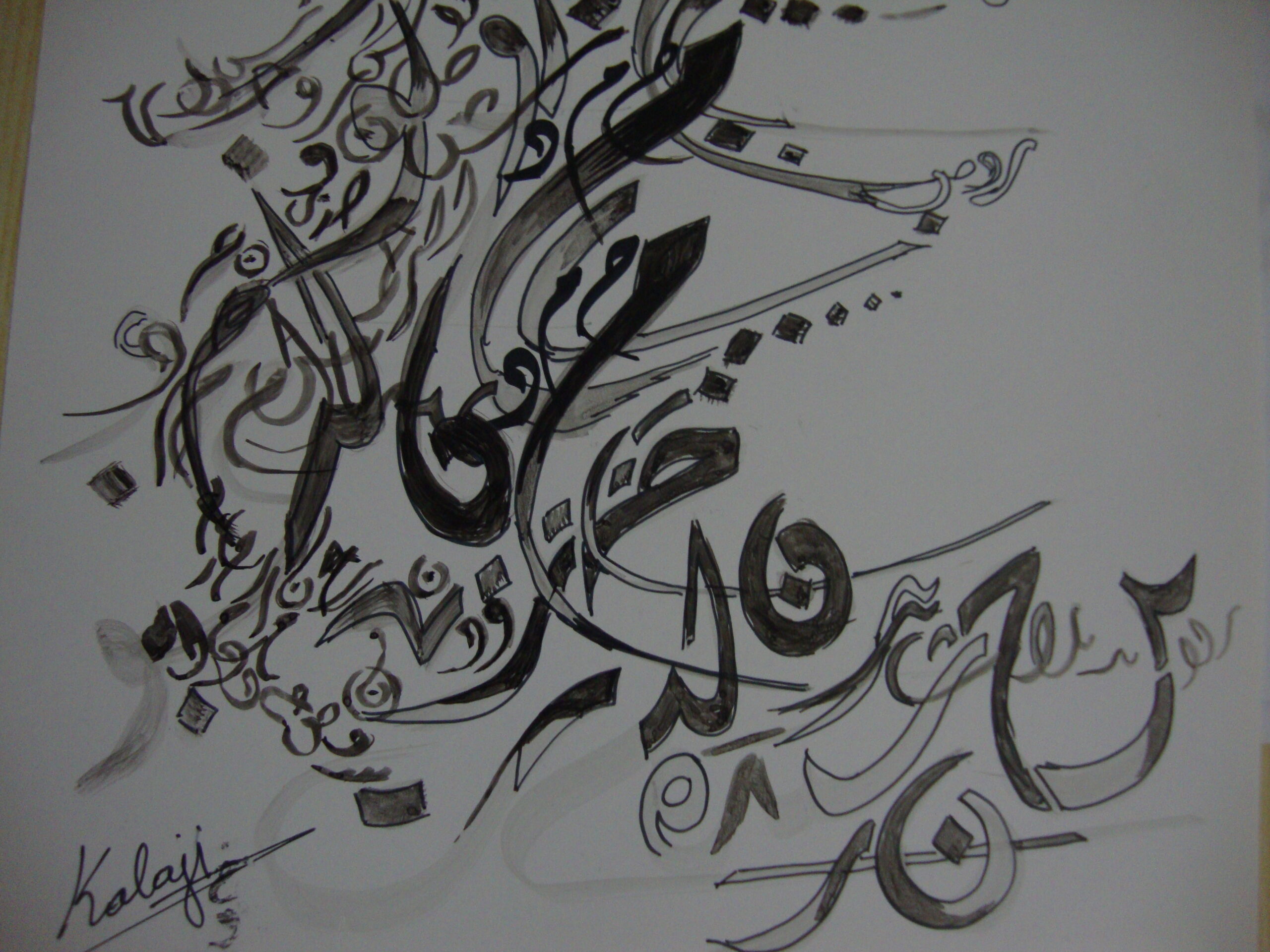
Visual Embedding of Calligraphic Ornamentation in Contemporary Art: A Dialectic of the Letter’s Memory and the Dynamics of Its Circulation
ملخص: تبدو الحروفية مسمى تشكيلياً بين الزخرفي والتصويري؛ فهي لا تتبع قوانين التأليف الزخرفي التقليدي لكنها تستفيد من خصائص الخط والزخرفة لإعادة الصلة بين اللغة والصورة. حرّر بعض الفنانين الحرف من وظيفته القرائية ليصبح عنصراً بصرياً مستقلاً، ما أثار جدلاً حول دوره التعبيري، علاقته بالزخرفة التقليدية، وإمكان إسهامه في سردية معاصرة للفن الإسلامي.
Calligraphy appear as a visual art form positioned between decorative and pictorial practices; it does not follow the rules of traditional decorative composition, yet it draws on the qualities of script and ornamentation to reconnect language with image. Some artists have liberated the letter from its reading function, turning it into an independent visual element, which has sparked debate about its expressive role, its relationship to traditional ornamentation, and its potential contribution to a contemporary narrative of Islamic art.
المقدمة
يفترض التضمين البصري لفنون الزخرفة حوارية نشطة، تقليدية / حداثية، مابعد حداثية ومعاصرة، للعناصر ذاتها المستخدمة في تقديم مفهوم مغاير ونوعي لفضاءات التشكيل الراهنة، فالأطباق النجمية كوحدة زخرفية متوارثة، هي ذاتها التي يتم تداولها حالياً على محامل ذات مواد وتكوينات مختلفة، كذلك طلاسم الحروفية المشتقة من الكتابة ” ولكنها كحروف مكتوبة ومبعثرة ليست أكثر من زخرفة، لطالما وصفت اللغة العربية من منظورات أوربية بأنها زخارف”[1]. أما المنمنمات الإسلامية فهي مجال تصويري ثري للقيام باستلهام مفرداتها الزخرفية تشكيلياً.
” لم يتصد الفن المعاصر لفن الماضي، ولم ينظر إلى الماضي بوصفه شيئاً ينبغي الظفر بالانبثاق منه، ولا حتى بوصفه مختلفاً تماماً كفن عن الفن الحديث عموماً، إن جزءاً من الفن المعاصر هو أن فن الماضي متاح لمثل هذا الاستعمال مثلما يحرص الفنانون على تقديمه”[2] وهو ما اشتغل عليه أكثر من فنان عربي معاصر، استطاع أن يحاور بعض تفاصيل الموروث التراثي، طالما هناك نقاط أو تشاركية شكلانية بين ما يطرحه التجريد الغربي من تبسيط واختزال وتركيبات حرة وصادمة، نراها موجودة داخل تكوينات المشهد الفني العربي الإسلامي، أكثر انضباطاً وميلا لهندسة المساحة، تقوم على التحوير والاختزال والتبسيط، ما يساهم في نشوء انزياحات دلالية، تبناها الفنان العربي وسيلة للخروج من استنساخ قوالب جاهزة مكررة للزخرفة عن طريق التجاوز والتوظيف الجديد وإعادة البحث في العلاقات التشكيلية بين عناصر الوحدة الزخرفية وعلاقة الوحدات الزخرفية ببعضها، داخل النسق التكويني والتأليفي للمنجز التشكيلي.
تبدو الحروفية مسمى تشكيلي يقع بين الزخرفي والتصويري لأسباب عدة، فهي ليست زخرفة لأنها لا تخضع لشروط التأليف الزخرفي المعروف في التراث العربي الإسلامي، لكنها تحمل بعض صفات الخط وبعض سمات الزخرفة في محاولة لإعادة الصلة بين اللغة والصورة، تجلّى ذلك في أعمال نجا المهداوي، شاكر حسن آل سعيد، رشيد قريشي وغيرهم، الذين حرّروا الحرف من وظيفته ( قابلية القراءة) ليصبح عنصراً تشكيلياً ذا هوية خاصة. بتوظيف الحرف العربي خارج وظيفته اللغوية التواصلية، داخل بنية تشكيلية بصرية ذات بعد جمالي معاصر، ماأثار جدلاً لايزال قائماً عن مشروعية تفكيك بنية الحرف رغم بعده عن آليات الزخرفة التقليدية وطرق تمثلها ، فهل الحروفية في بعدها التجريدي الغنائي والتصوفي أكثر تعبيراً من نصوص الزخارف الخطية المقروءة؟..وهل اكتفت الحروفية من التكرار النمطي لتشكيل للمساحات؟..وهل مازال دورها التأملي والتواصلي قائماً أو اكتفت بإشغال الفراغ أو زينته؟…وهل غيرت الحروفية وحفرت في ذاكرة الحرف العربي استلهاماً وتشوقاً وتواصلاً تراثيا بهدف تأسيس سردية معاصرة للفن الإسلامي ؟…أم أنها ذات بعد توفيقي وتلقيطي ؟…
بقيت إشكالية تغيير دلالة الحرف العربي وعزله عن سياق نشأته، تثار من زوايا عدة أولها التضحية بالمعنى والمقروئية مع إمكانية إنجاز لوحات خطية تنافس تكوينات الحروفية، لنا في ذلك الخطاط التونسي عامر بن جدو، عمر الجمني، طارق عبيد، صفوان ميلاد. وهم خطاطون وحروفيون معاصرون زمنياً للجدل الأبدي حول الخط العربي وحروفه، أما أساليب التداول فقد عرفت تطوراً زمكانياً يمتد إلى الفترة العثماني واختراع الطباعة ” وعندما دخلت الطباعة عاصمة الخلافة العثمانية، قام الخطاطون بتظاهرة جنائزية، فحملوا ستاراً أسود ووضعوا أقلامهم ومحابرهم عليه، كأنهم يسيرون بالخط إلى مثواه الأخير”[3]، فهل فعلت الحروفية ذلك في عصرنا الحالي؟… تعتبر الفترة العثمانية ذروة الإبداع في اللوحات الخطية المزخرفة والمذهبة وابتكار أنواع الخطوط وتنافس الخطاطين، لكن مع الطباعة خفت وهج الإبداعات الخطية وكأنها استقرت ” ومما يورث الأسف بعد ذلك، أن التنميق الإسلامي تحدر، على تعاقب السنين، إلى ركام من رواسم مطروقة أي طرق حتى همدت وخوت وكان ذلك المصير محتوماً، إذ هو تمنع أن يتجدد من الباطن، ثم أن التجريد المفرط مساقه إلى الركاكة”[4] هكذا وصف بشر فارس تحدي التنافس الجمالي بين الخطاطين المنمقين، الذين اتهمهم بالنمطية في نتاجهم الفني، وعدم التجدد، مايفسر الطفرة الجمالية المعاصرة للحروفية العربية في سعيها الحثيث لتأثيث الفضاءات والمحامل( معدن ، خزف، عمارة، خشب محفور، قماش، جص) والمجازفة عبرمفاهيم الحداثة والمعاصرة بتمردها على المألوف تشكيلياً.